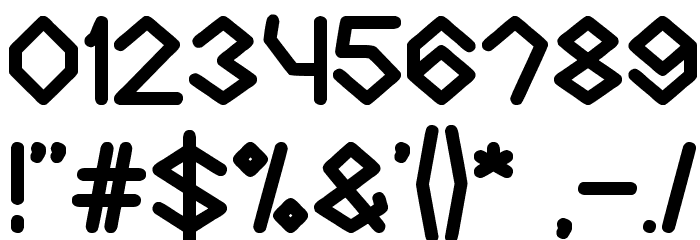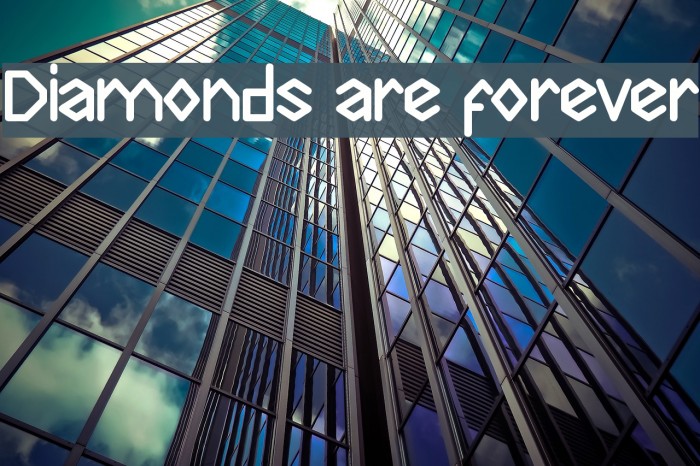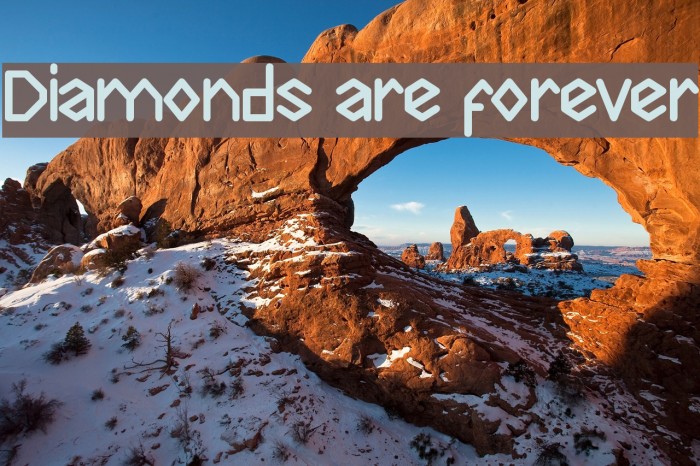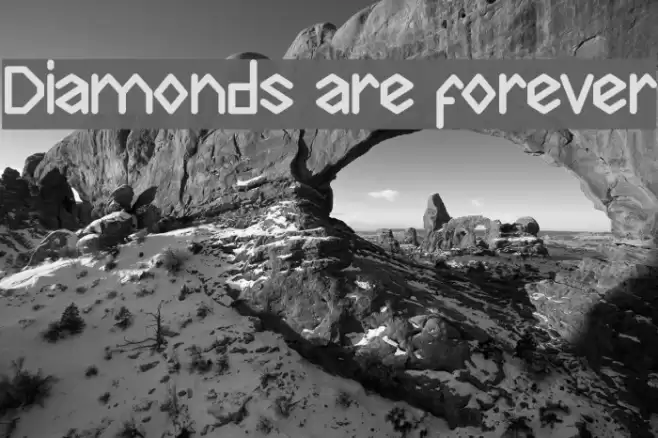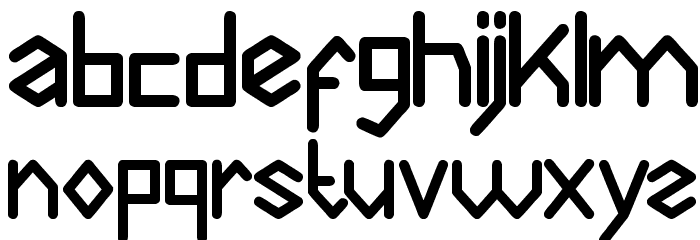
Diamonds are forever Font
✎ Futuristic
| Kategorien | Futuristic |
| Gesamtstil | Futuristic |
| Vorgeschlagene Projekte | Ideal for technology-themed projects, sci-fi movie posters, video game titles, or branding for tech companies. |